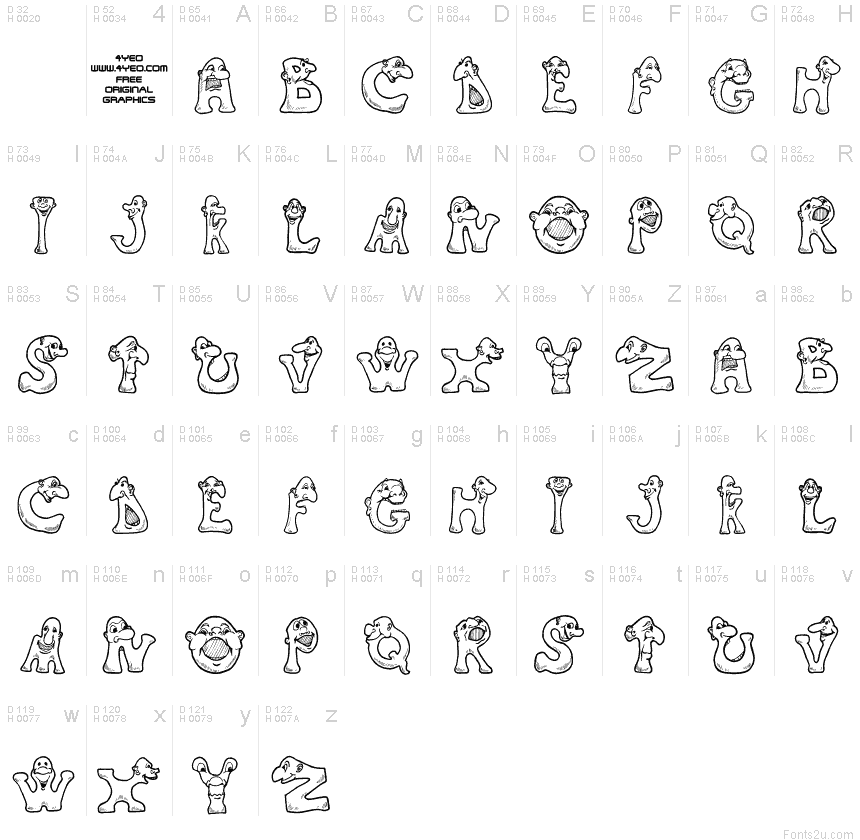
4YEO Monstrum di 4YEO è un carattere display gratuito in stile cartoon, dove ogni lettera si trasforma in un piccolo mostro buffo. Ogni segno è disegnato a mano con contorni traballanti, occhi sporgenti e una texture scarabocchiata, rendendo il testo vivo, come se strisciasse, salutasse e sorridesse sulla pagina. Il look è giocoso e un po' caotico, come i disegni a margine di un amato quaderno di schizzi.
Usando 4YEO Monstrum, i titoli diventano immediatamente una parata di piccole creature che catturano l'attenzione dei bambini (e dei bambini grandi). Questo font gratuito funziona a meraviglia per copertine di libri per bambini, poster di Halloween vischiosi e spaventosi, inviti per feste, materiale scolastico, titoli di giochi e set di adesivi. Per la leggibilità, mantienilo grande e usa un carattere sans serif pulito per il testo principale: lascia che siano i mostri a occuparsi di tutto il divertimento.